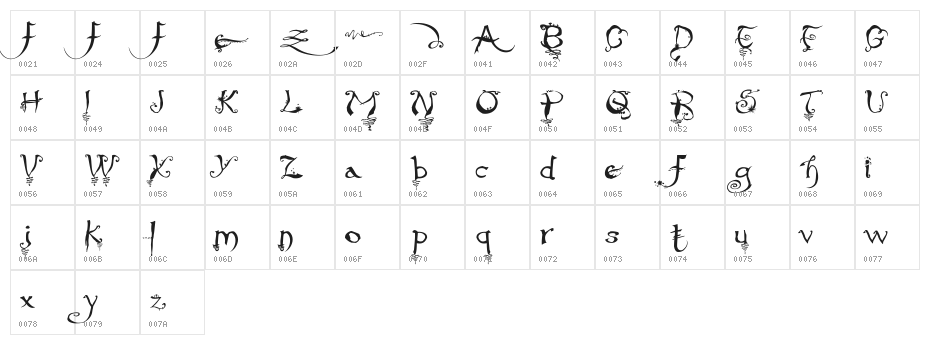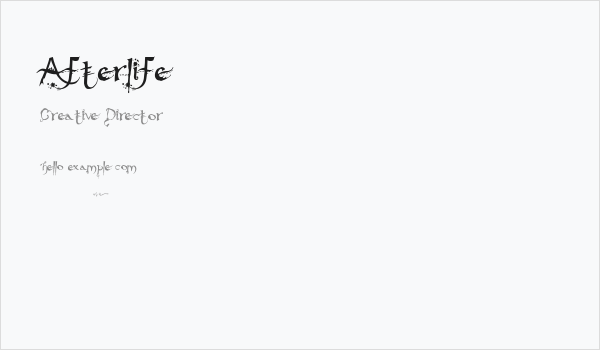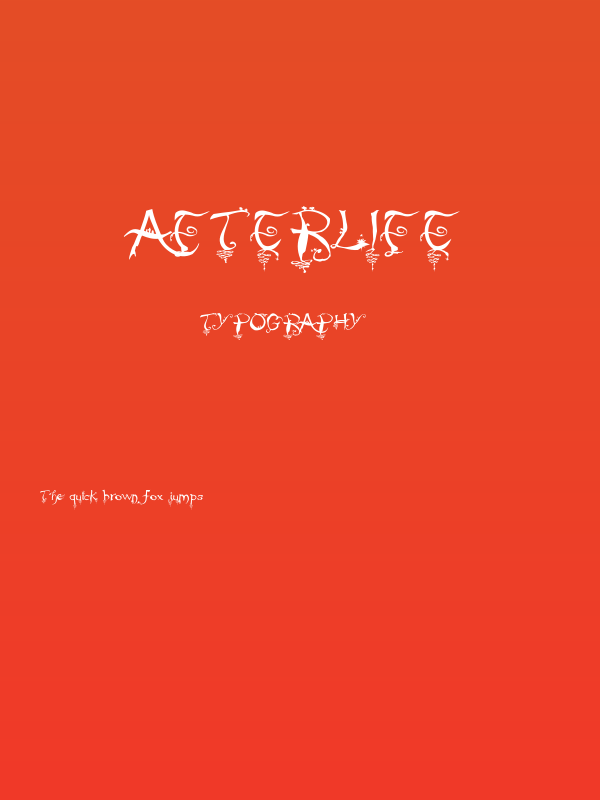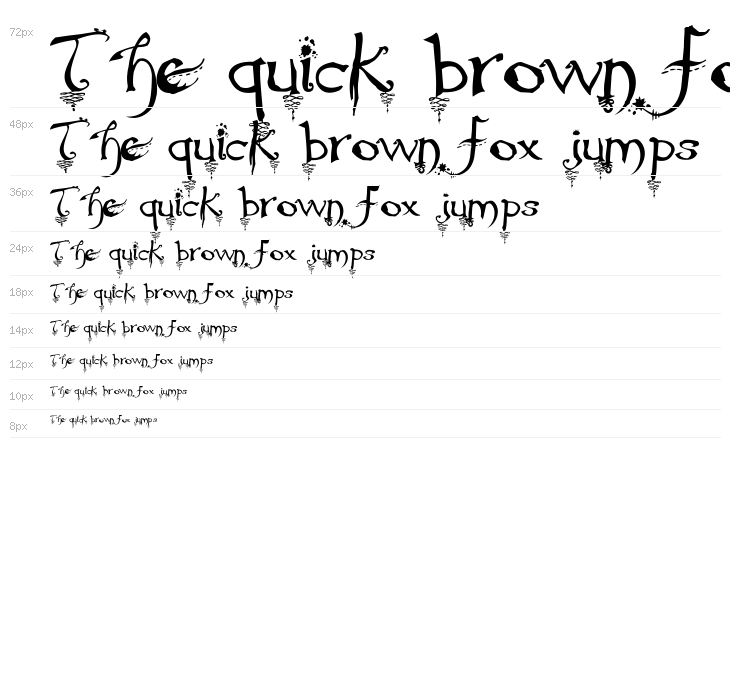
Afterlife Font
| Gesamtstil | Gothic, Whimsical, Decorative |
| Vorgeschlagene Projekte | Ideal for fantasy book covers, Halloween event posters, gothic-themed invitations, or any project requiring a dramatic and artistic touch. |